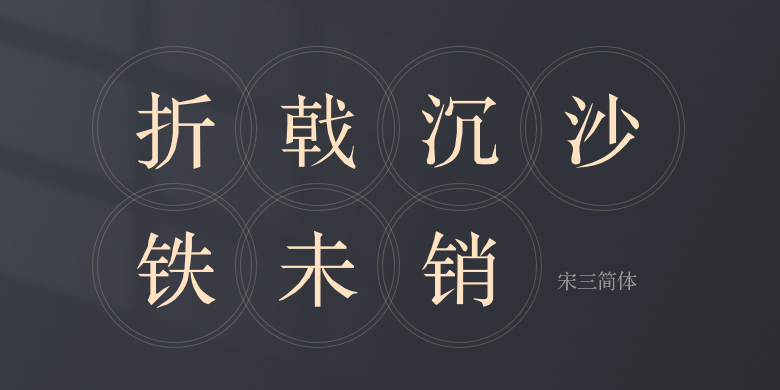
宋三简体
宋三简体,这款字体结构工整、笔画清晰,兼顾美观与易读性,适用于标题、正文、海报、包装、LOGO 等多种场景。字形优雅稳定,风格百搭耐看,适配日常排版与创意设计,让文字呈现更舒适、更具质感。宋三简体一笔一画,皆是细节,以均衡的比例、流畅的线条打造舒适视觉体验,字形端正大气,风格简约现代。无论是商业设计、品牌宣传还是日常排版,都能轻松驾驭,让文字更有格调与力量。宋三简体字体下载。